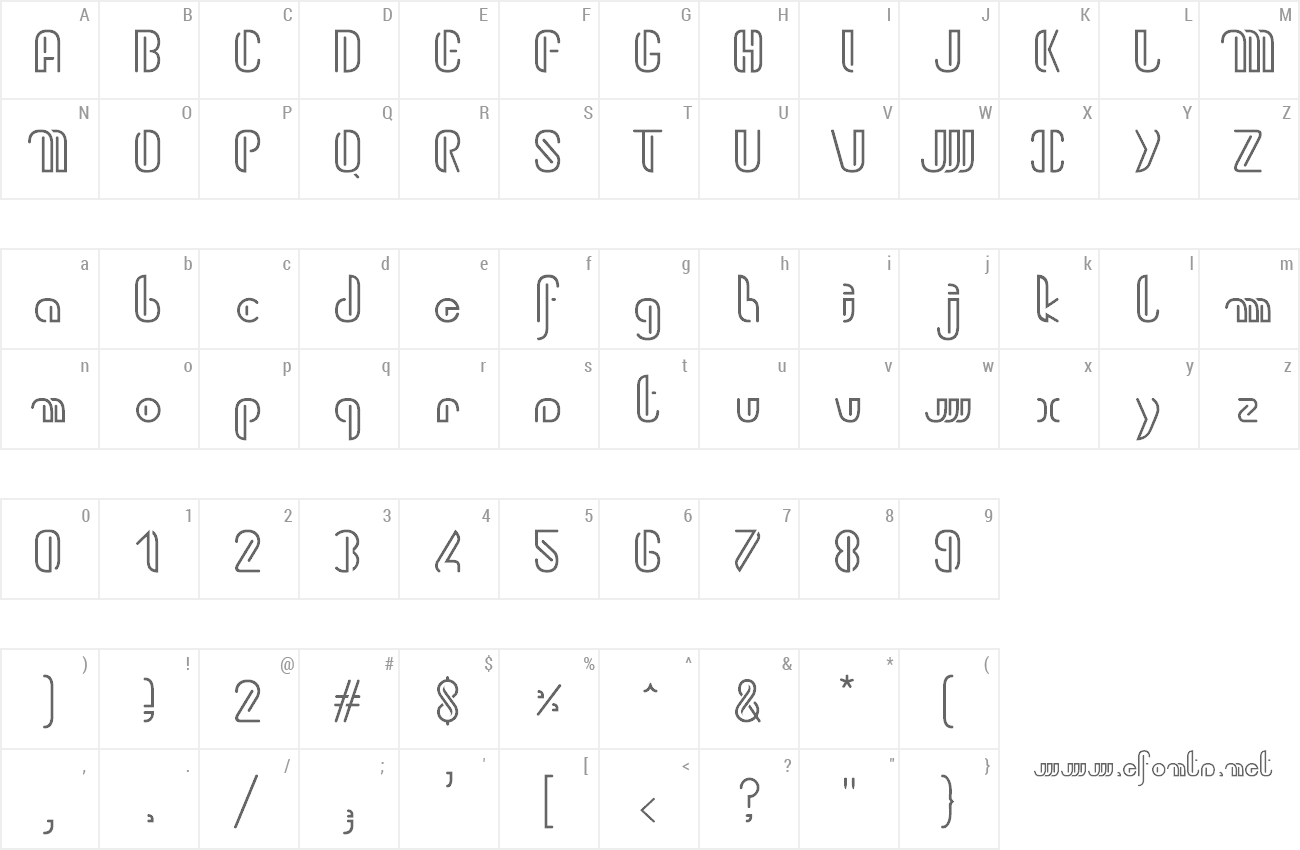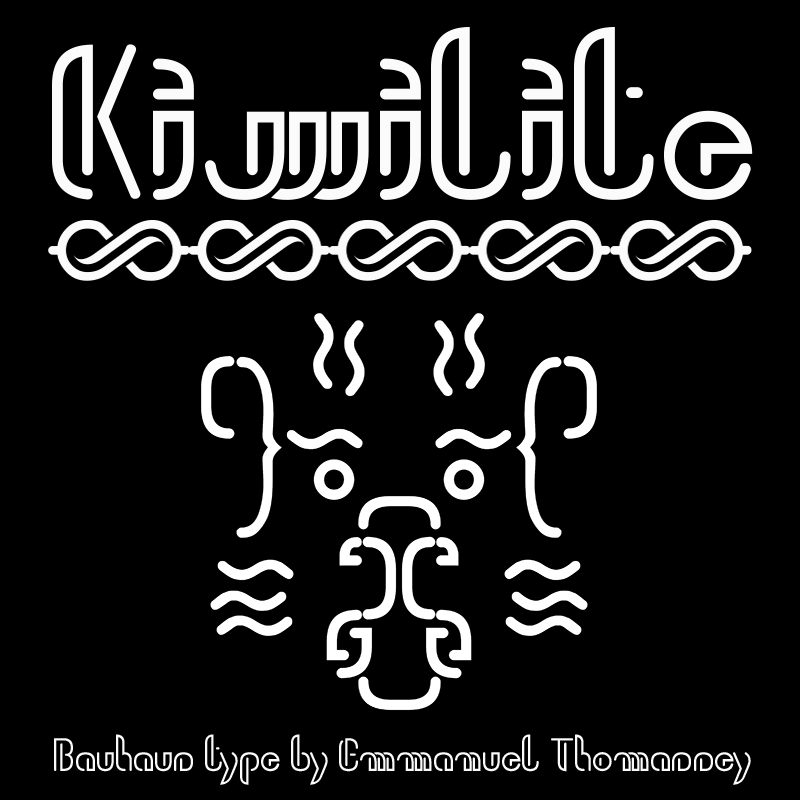
| Font name: | Kiwilite |
| Author: | Emmanuel Thomassey |
| Note by Emmanuel Thomassey | |
| M�me police que "Kiwi" mais avec les extr�mit�s arrondies. |